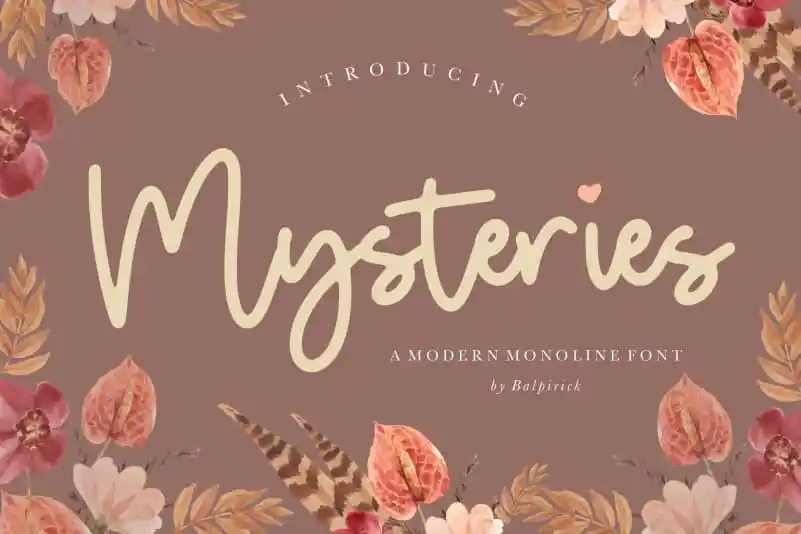
Mysteries Monoline Font
A fonte ‘Mysteries Monoline Font’ é perfeita para quem busca uma tipografia assertiva e minimalista que se destaca no cenário do design. Ideal para projetos como embalagens de produtos, identidade visual, revistas ou mesmo para destacar mensagens em redes sociais, o Mysteries oferece um toque elegante que combina perfeitamente com elementos de fundo mais elaborados. Este estilo único e contemporâneo é especialmente apropriado para criações criativas como casamentos, onde pode ser usado para escrever no topo de uma imagem ou foto, criando um contraste visual impressionante e dando vida à sua mensagem. Seja você um designer gráfico, empreendedor digital ou especialista em design editorial, o Mysteries Monoline é a escolha perfeita para dar seu projeto aquele toque inovador e sofisticado que faz toda a diferença no mercado moderno da design.